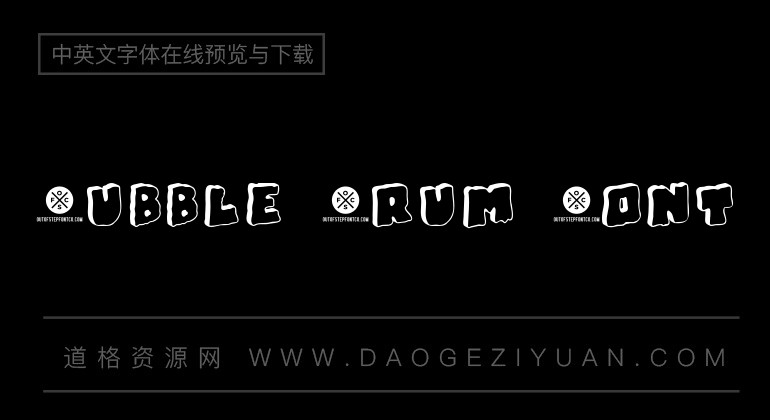
Bubble Frum Font 是一种有趣的字体,它的设计灵感来自于气泡字母和手写字体的结合。该字体的每个字母都被设计成由一系列气泡形状组成,使得它看起来像是在水中漂浮的气泡一样。每个字母都有自己独特的气泡形状和大小,使得 Bubble Frum Font 具有非常有趣和独特的外观。 Bubble Frum Font 可以用于各种设计场景,比如海报、广告、标志、书籍封面等等,特别是与涉及到儿童、游戏和娱乐等领域的设计非常相配。此外,由于该字体的形状和线条非常清晰,因此非常适合在较小的字号下使用,比如在手机应用程序或网站中使用。 总之,Bubble Frum Font 是一种非常有趣和独特的字体,可以为各种设计场景增添一份趣味和独特性。内容介绍
Bubble Frum Font是一款非常不错的手写艺术字体,具有很好的视觉感,适合于文化类的宣传设计、商业类品牌的广告和产品包装设计以及个性化文字排版等较多场景。